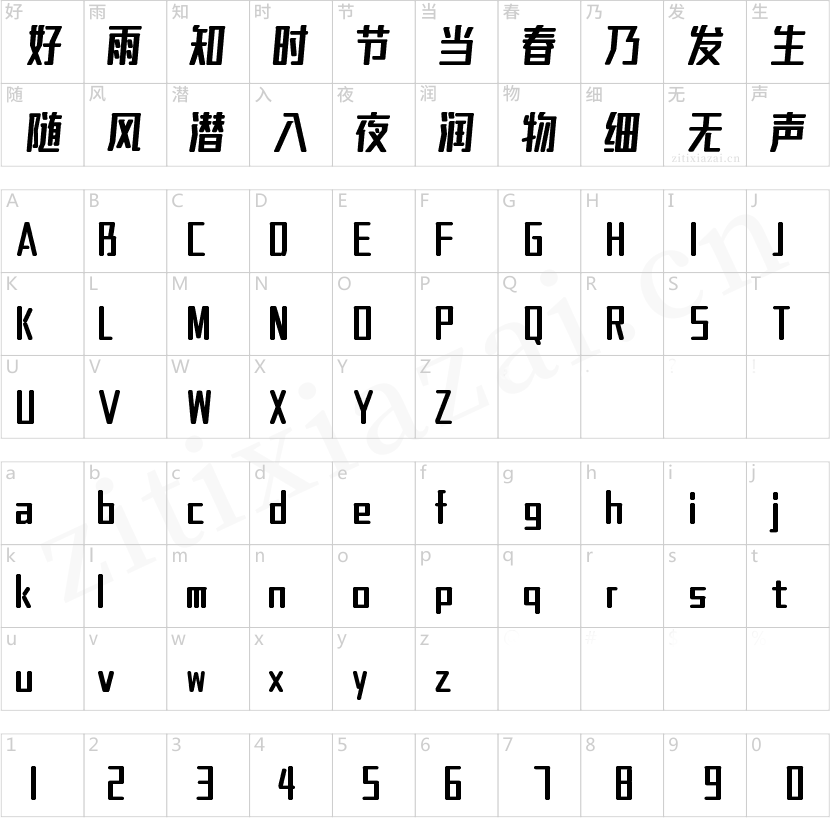
字魂笔记体
字魂笔记体,这款字体结构工整、笔画清晰,兼顾美观与易读性,适用于标题、正文、海报、包装、LOGO 等多种场景。字形优雅稳定,风格百搭耐看,适配日常排版与创意设计,让文字呈现更舒适、更具质感。字魂笔记体一笔一画,皆是细节,以均衡的比例、流畅的线条打造舒适视觉体验,字形端正大气,风格简约现代。无论是商业设计、品牌宣传还是日常排版,都能轻松驾驭,让文字更有格调与力量。字魂笔记体字体下载。
字魂字体字魂笔记体字体是由字魂创意字库设计并生产的一款可商用的字体,被收录于字魂先锋系列。该字体支持GB-2312标准,包含6942个中文、字母、符号和数字,字体类型偏向黑体,具有简约、时尚的风格,在市面上广泛用于公益宣传、海报企宣、荣誉证书等场景。